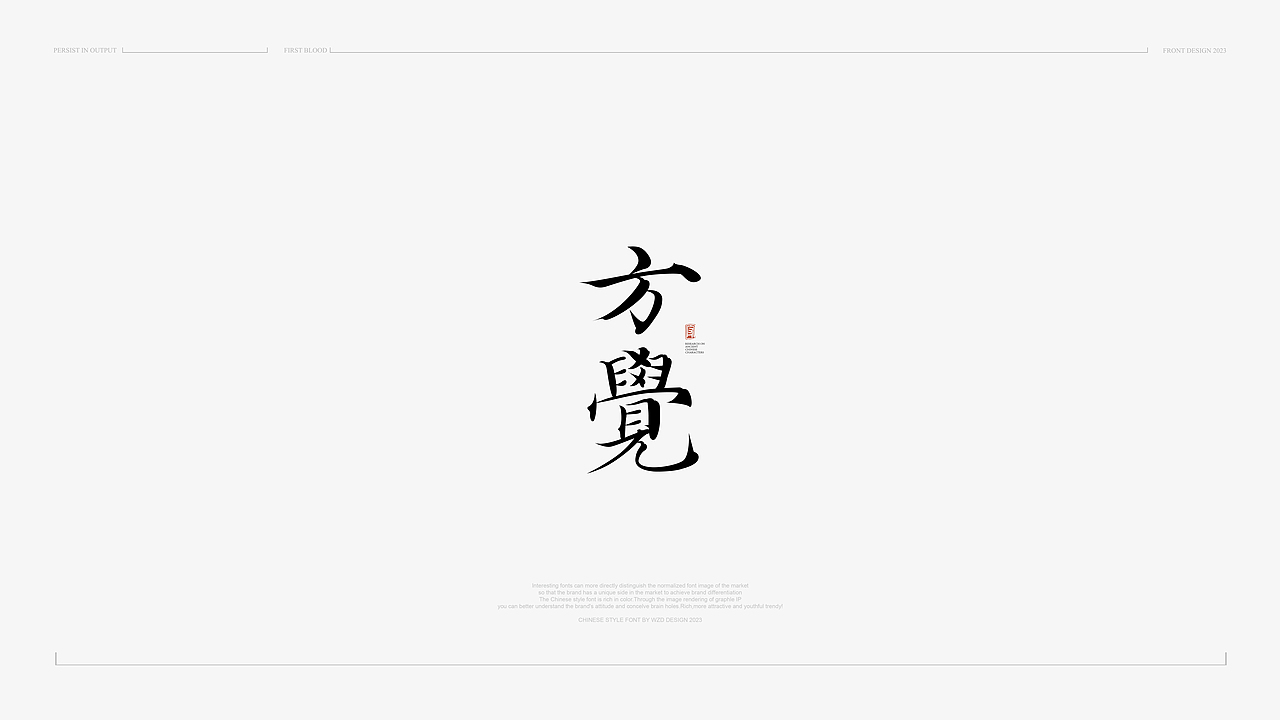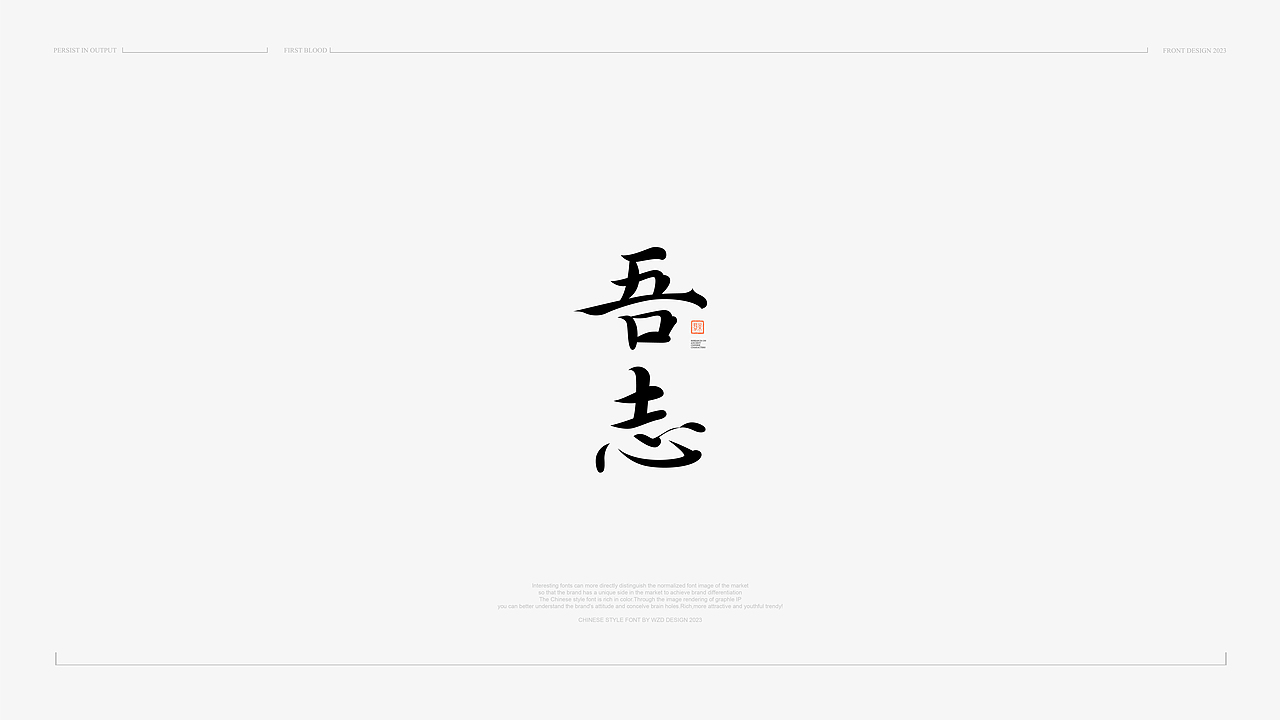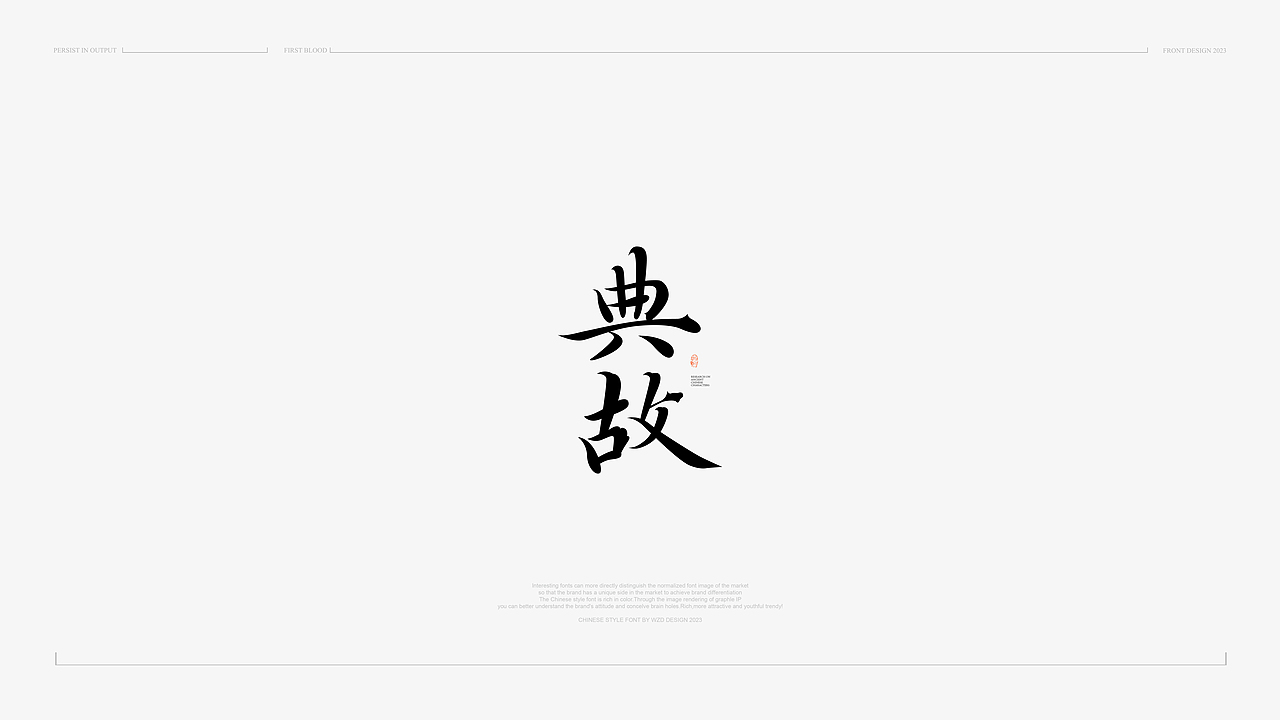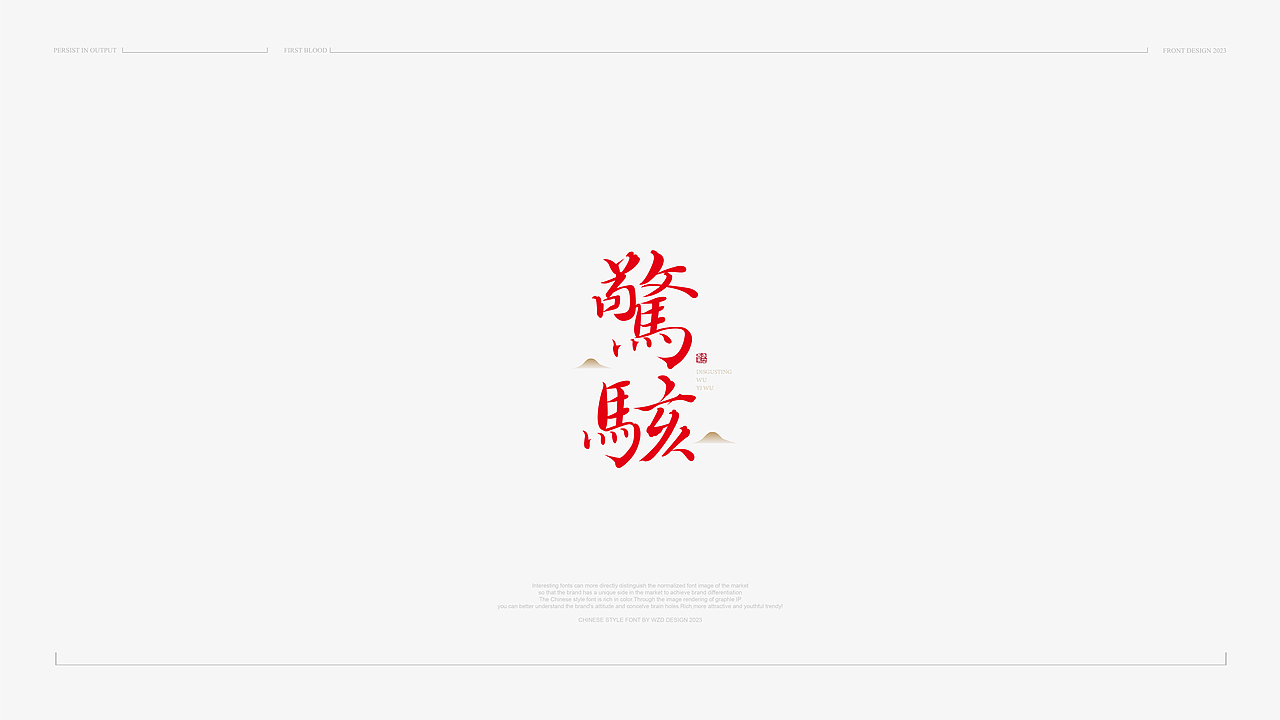
中国风&字体设计丨2023字体标志10月新篇章
唯自渡
古字新说-手写字体设计/2023.10.12
古风字体/字体设计
学而时习之,不亦说乎?
有朋自远方来,不亦乐乎?人不知而不温,不亦君子乎?
Isn't it also said to learn and practice from time to time? Isn't it a pleasure to have friends coming from afar? Is it not a gentleman who knows nothing but is not warm?